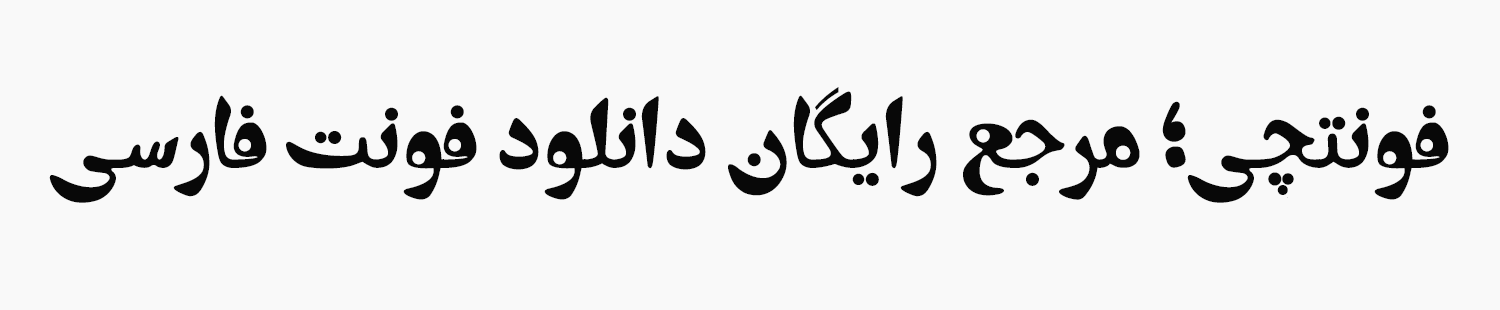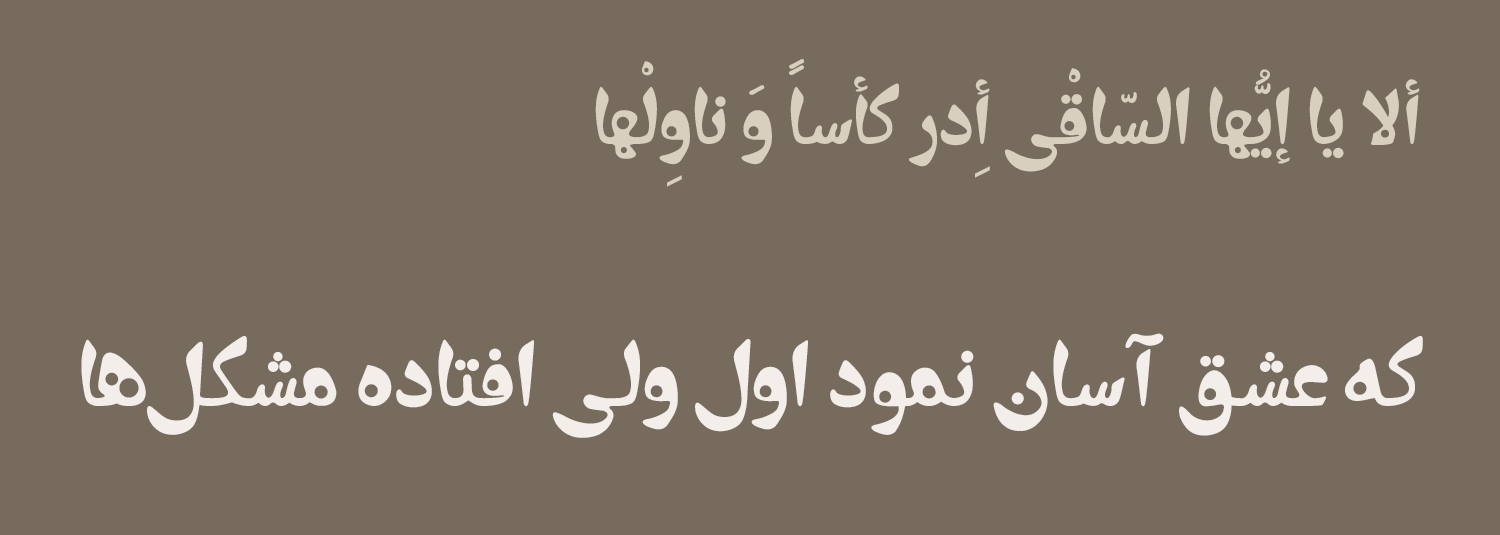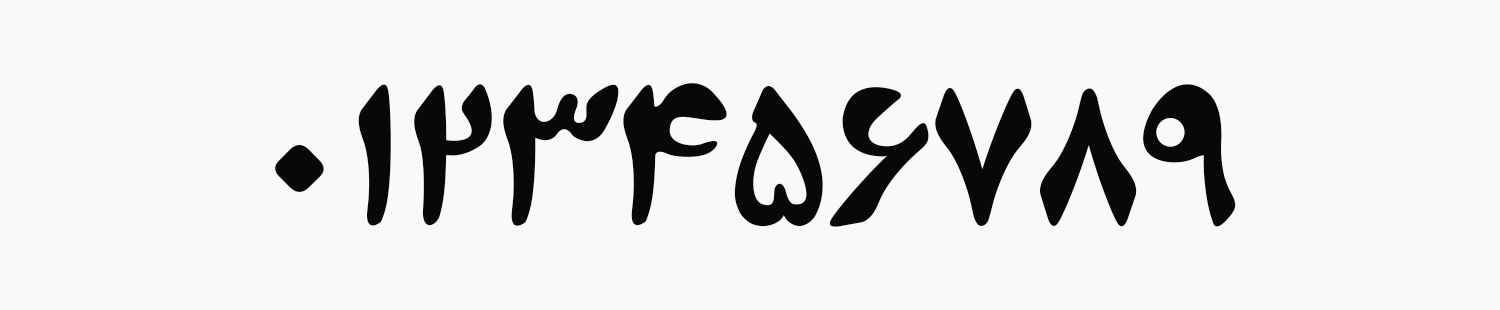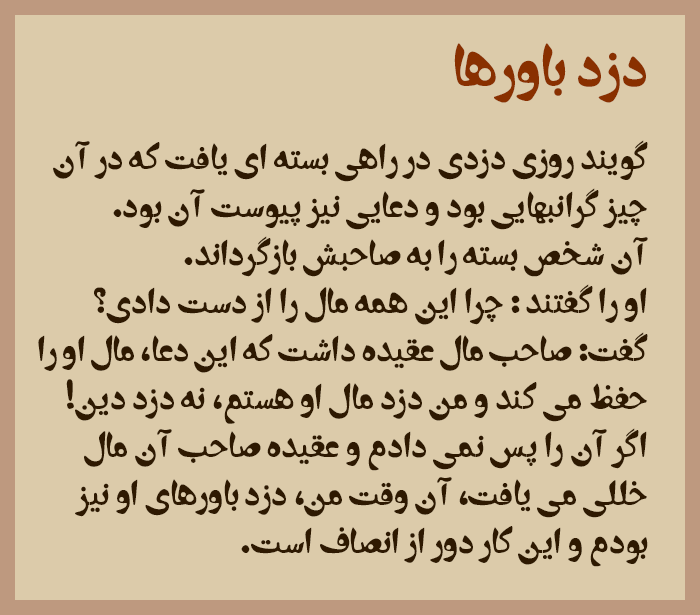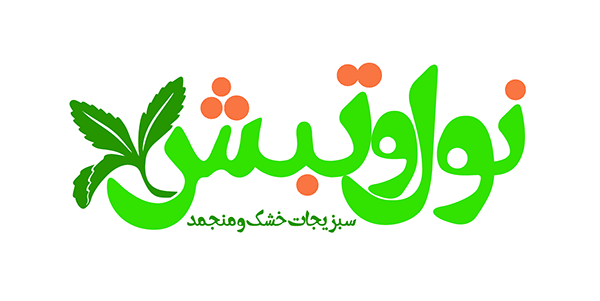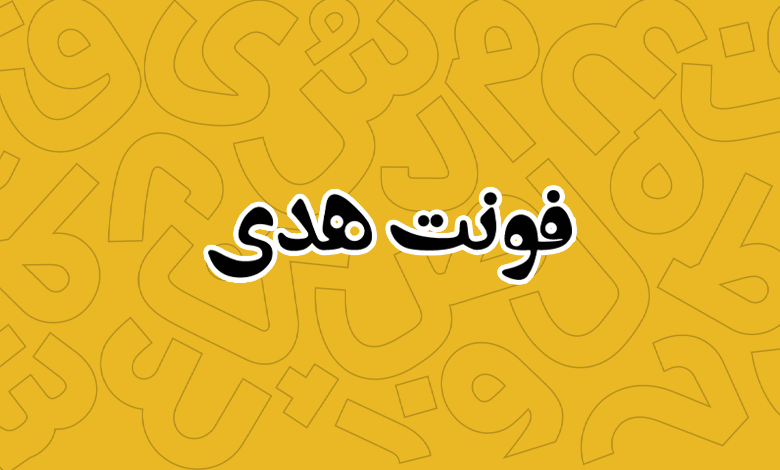
فونت هدی (Hoda)
فونت هدی (به انگلیسی: Hoda) یک فونت رایگان فارسی در گروه فونتهای فانتزی است که با الگوبرداری از خط نسخ طراحی شده است. از این قلم با توجه به سبک خاصی که در حالت چشمیها، ضخامت حروف، منحنی و خلوط شکسته دارد میتوانید برای کارهای گرافیکی فانتزی استفاده کنید.
هدی ترابی خواه طراح این قلم، آن را با الگو گرفتن از دو فونت تیتر و زر بولد ایجاد کرده است که هر دو قلمی بر پایه خط نسخ هستند. تغییرات در این دو قلم آنقدر جسورانه و اغراقآمیز بوده که به سختی میتواند اثری از دو فونت مورد نظر را در آن پیدا کرد.
در ادامه این نوشته از سایت فونتچی به نقد و بررسی فونت هدی رایگان خواهیم پرداخت. قلمی که در عین ساختار فانتزی خود میتواند در حوزههای مختلفی بهویژه کودک و نوجوان برای طراحی کتب و مجلات، لوگو تایپهای غیررسمی و کارهای فانتزی که جنبه نمایشی دارند مورد استفاده قرار گیرد.
بررسی و دانلود فونت هدی ترابی خواه (Hoda Torabikhah)
از فونت هدی بیشترین استفادهای که میتوانید داشته باشید برای عناوین و متنهای کوتاه است؛ چرا که این قلم ساختاری فانتزی داشته و از آن مهمتر اینکه بخاطر ظاهر متفاوت چشمیها، دندانهها و ضخامت حروف در اندازههای بزرگ خود را بهتر نشان خواهد داد و نمایشیتر بهنظر میرسد.
اما بدان معنا نیست که نتوانید برای متون بلند از آن استفاده کنید. استفاده برای قصههای کودکانه در کتابهای مصور یکی از کاربردهای خوب این قلم است که تاکنون زیاد هم در صنعت چاپ و مطبوعات برای همینمنظور مورد توجه قرار گرفته است.
سبک طراحی و وزن فونت هدی
همانطور که اشاره شد فونت هدی ترابی خواه، با استناد بر دو فونت تیتر و زر بولد ساخته شده است. با تلفیق این دو قلم و ایجاد تغییرات اساسی در بخشهای مختلف حروف شاهد تولد فونتی فانتزی هستیم که تغییراتی بسیار جسورانه داشته است.
در این قلم حروف در بخشهای ابتدایی و انتهایی دارای ضخامت بیشتر بوده و در عوض میانه حروف ضخامت کمتری دارند. منحنیها بر خلاف سایر قلمها از حالت رسمی تبعیت نکرده و دارای کشیدگی دلخواه خود هستند و در پایان چشمیها نیز از یک ساختار خاص پشتیبانی نمیکنند.
پشتیبانی از زبان فارسی و رسم خط های تابعه
در حالت کلی فونت هدی فقط از زبان فارسی پشتیبانی کامل و استانداردی دارد. کلیه حروف فارسی در این قلم از همان سبک فانتزی برخوردار بوده و با قرارگیری در کنار یکدیگر این فونت فانتزی را تکمیل کردهاند.
اما از آنجا که زبانهایی نظیر عربی، کردی و ترکی نیز از رسم خط فارسی برخوردار هستند میتوانید از این قلم در سایر زبانهایی که مبتنی بر حروف فارسی هستند استفاده کنید. ولی باید به این نکته توجه کنید که پشتیبانی در سایر زبانها کامل نیست.
به عنوان مثال در زبان عربی که حروف «ک، ی، ه، ؤ، ئ» از نظر قرارگیری نقطه و همزه بر روی حروف متمایز از فارسی هستند دارای گلیف اختصاصی نیستند و تنها به کمک برنامههای گرافیکی میتوانید برخی از این کاراکترها را به این حروف اضافه کنید.
یا در زبان اردو حروف «ﮧ، ﮩ، ے» که متفاوت از نسخه فارسی است اصلا دارای گلیف نیستند و از نسخه فارسی هم استفاده نخواهد شد؛ مگر اینکه چنین حروفی را در حالتی که صفحه کلید روی زبان فارسی باشد تایپ کنید. این قلم از فونت انگلیسی پشتیبانی نمیکند.
دارای اعداد استاندارد فارسی
ویژگی دیگر قلم هدی پشتیبانی از اعداد استاندارد فارسی است. میتوانید با تایپ اعداد در حالتی که صفحه کلید فارسی باشد اعداد را با همان سبک فانتزی مانند تصویر زیر تایپ کنید.
اعداد در فونت هدی بهصورت اعداد هک شده هستند. یعنی حتی زمانی که شما از زبان انگلیسی یا بخش ماشین حساب صفحه کلید برای تایپ استفاده کنید، همچنان فارسی تایپ خواهند شد و مشابه چیزی که در بخش زبان دیدیم، فاقد اعداد انگلیسی است.
فونت صمیمی و مناسب کودک و نوجوان
با توجه به ساختار فانتزی فونت رایگان هدی، از این قلم میتوان برای کارهایی که جنبه صمیمی دارند استفاده کرد. از همینرو استفاده از آن برای کتاب، مجلات و کمیکهای کودک و نوجوان میتواند بهترین گزینه باشد.
خوانایی این فونت با توجه به ضخامتی که دارد برای کودکان با سن پایین انتخاب خوبی خواهد بود. چه برای زمانی که از این قلم در طراحی جلد با فونت درشت استفاده کنید و چه برای متنهای طولانی از فونت با اندازه استاندارد استفاده کنید، ساختار صمیمی که دارد، آنها را به خواندن قصههای کودکانه علاقهمند خواهد کرد.
مناسب برای ساخت لوگو فانتزی
دیگر کاربردی که فونت هدی میتواند داشته باشد، برای طراحی لوگو تایپ فانتزی است. به کمک کمی خلاقیت میتوانید از این قلم برای ساخت لوگو تایپهایی که جنبه صمیمی دارند استفاده کنید.
عموما لوگوهایی که میتوانید با این قلم طراحی کنید نیز میتواند در حوزه کودک و نوجوان بوده یا اینکه فروشگاههای سطح شهر باشد که لوگو را بر روی تابلو و سردر مغازه نصب کنید.